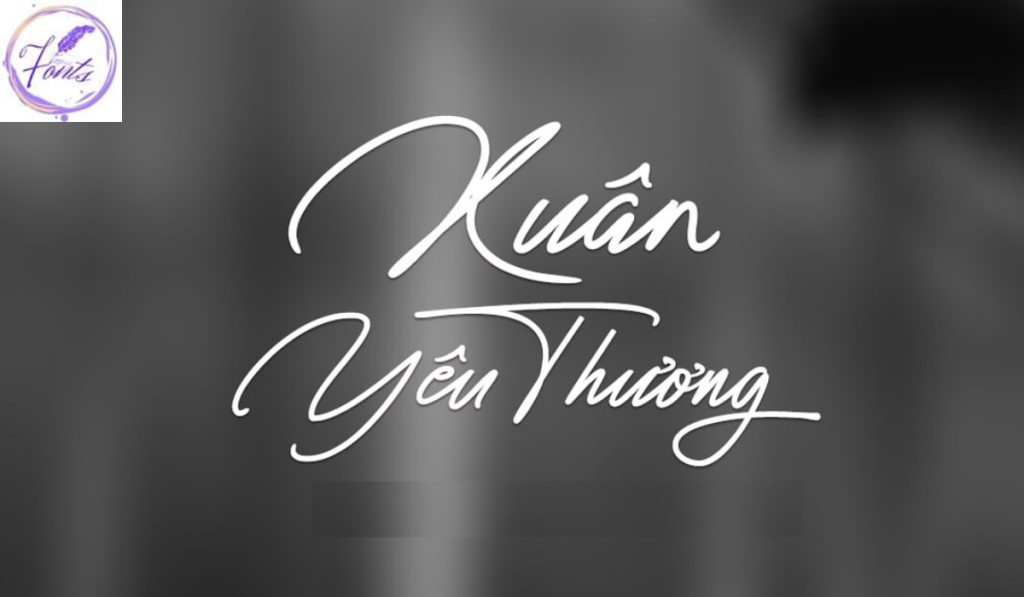
Font chữ uốn lượn việt hóa
Ngôn ngữ: Tiếng Việt và một số ngôn ngữ khác
Bộ Font: Đa dạng
Phân loại: Uốn lượn, cá tính
Kiểu chữ: Script, viết tay
Độ dày: Thin, ExtraLight, Light, Regular, Medium
Đánh giá font chữ uốn lượn Việt hóa
Bộ sưu tập font chữ uốn lượn việt hóa của Fonts.com.vn đã nhận được sự đánh giá cao từ cộng đồng thiết kế đồ họa và chuyên gia typography. Với sự kết hợp hoàn hảo giữa tính thẩm mỹ và tính ứng dụng, các font chữ của chúng tôi đã được sử dụng rộng rãi trong nhiều lĩnh vực như thiết kế logo, bao bì sản phẩm, thiệp cưới, và thậm chí cả trong các dự án phim ảnh. Nhiều khách hàng đã gửi phản hồi tích cực về chất lượng và sự đa dạng của bộ sưu tập glyph font, đồng thời đánh giá cao sự hỗ trợ nhiệt tình của đội ngũ chúng tôi. Với Fonts.com.vn, bạn có thể hoàn toàn yên tâm về chất lượng và sự hài lòng khi sử dụng font chữ uốn lượn việt hóa.